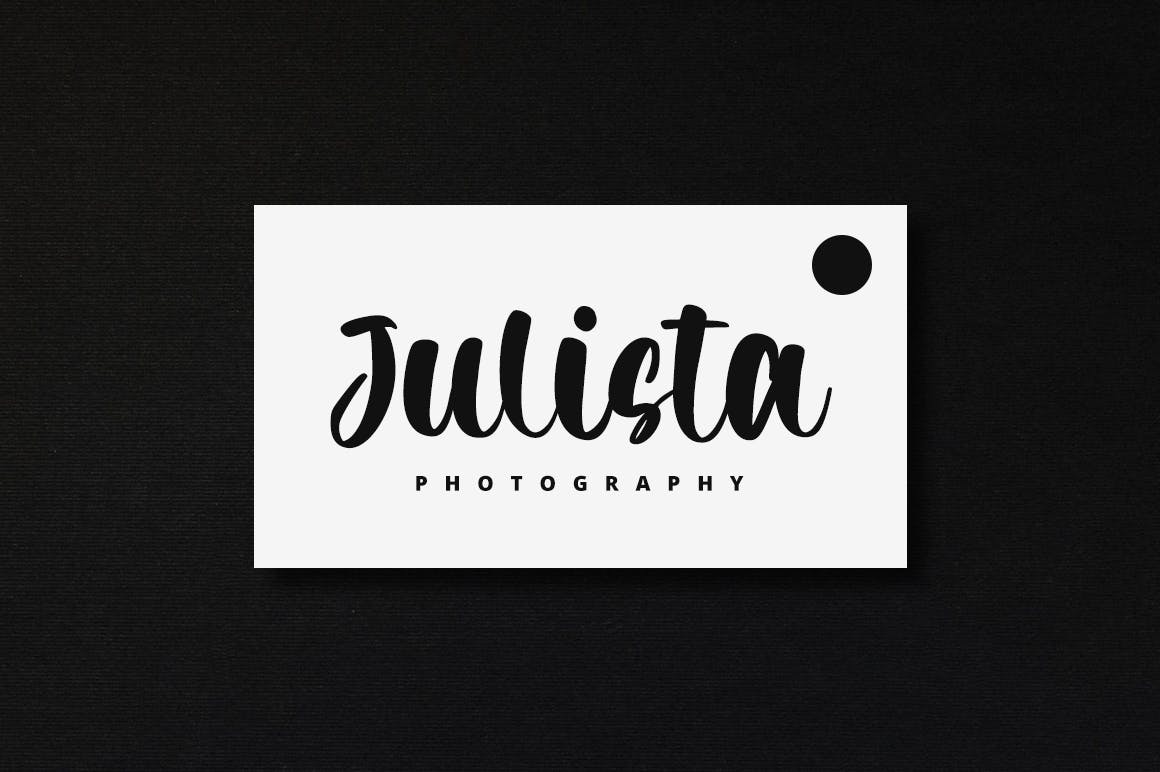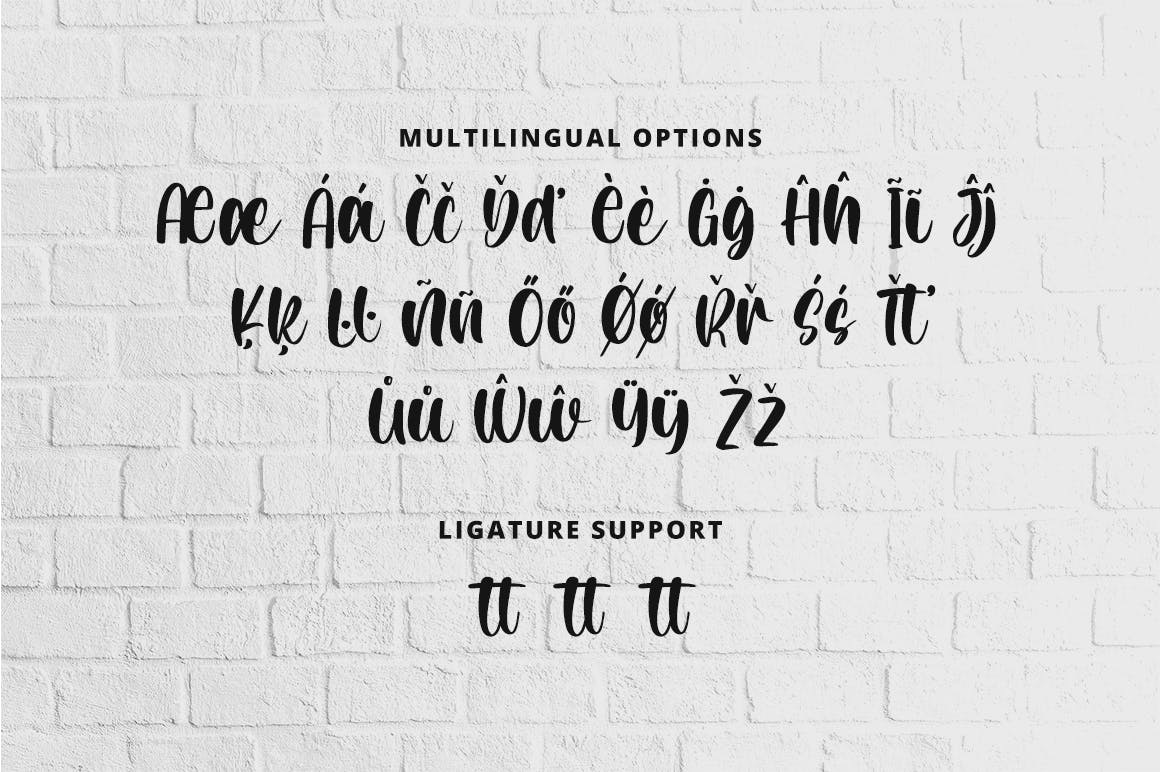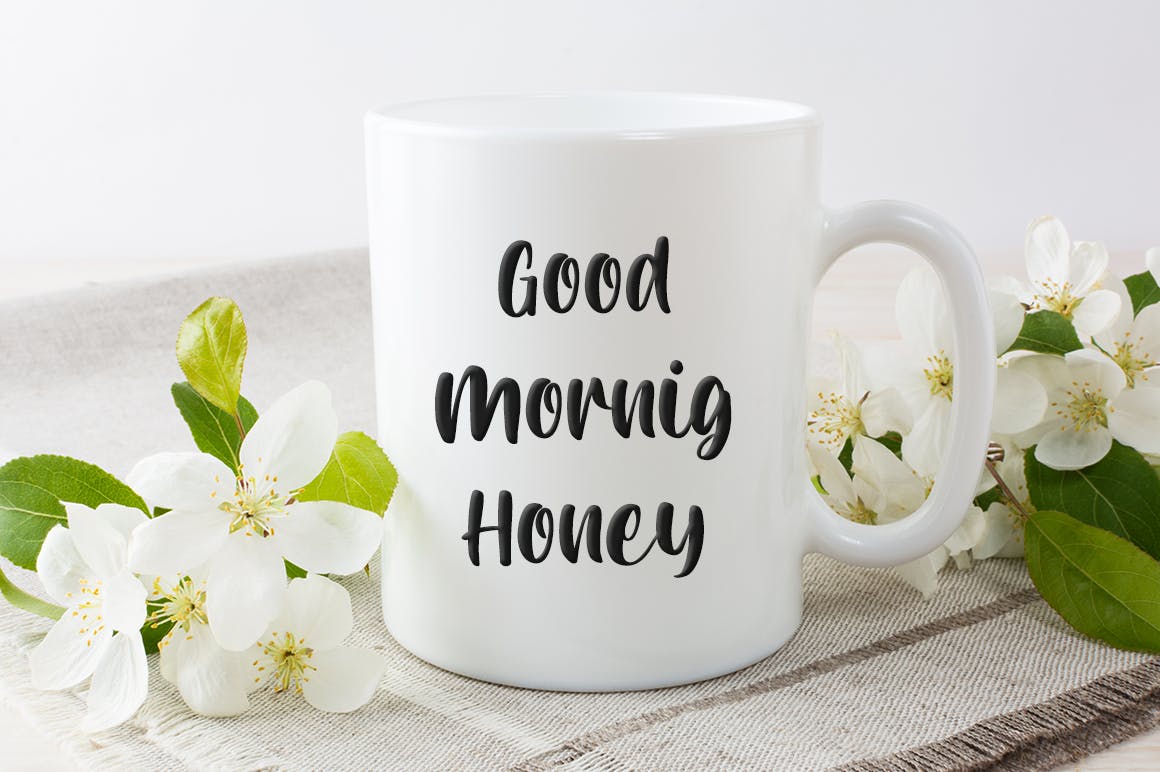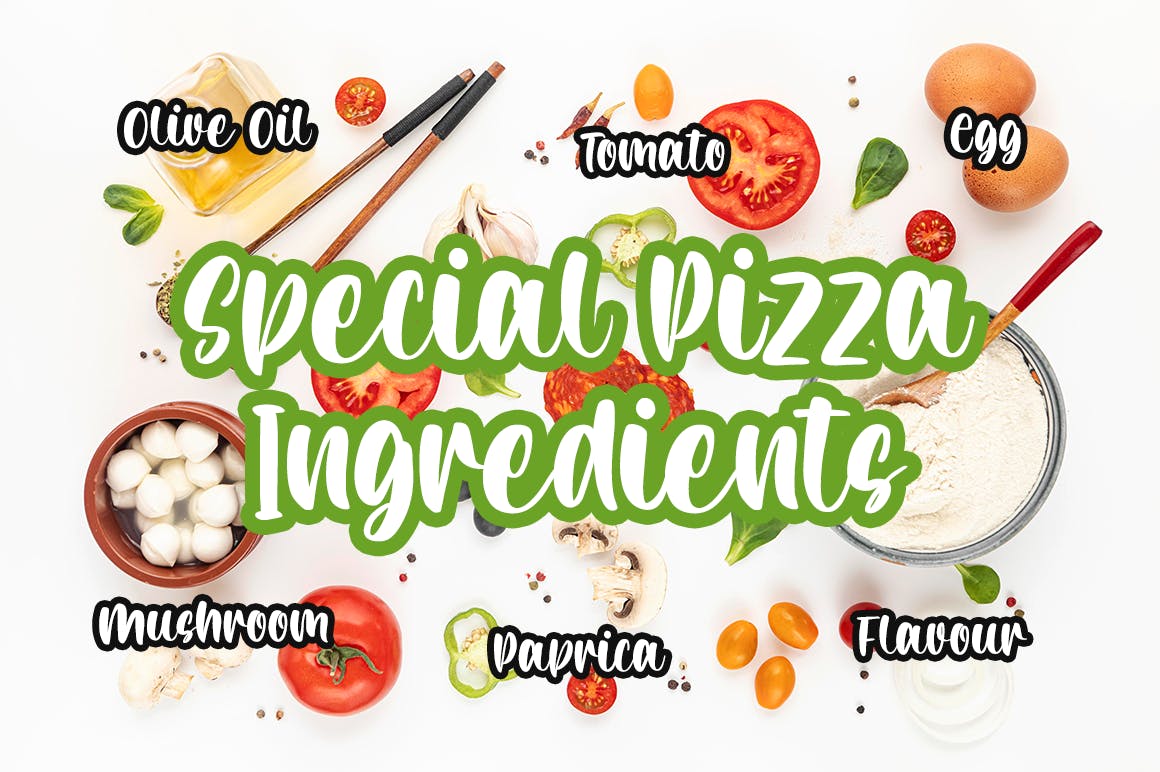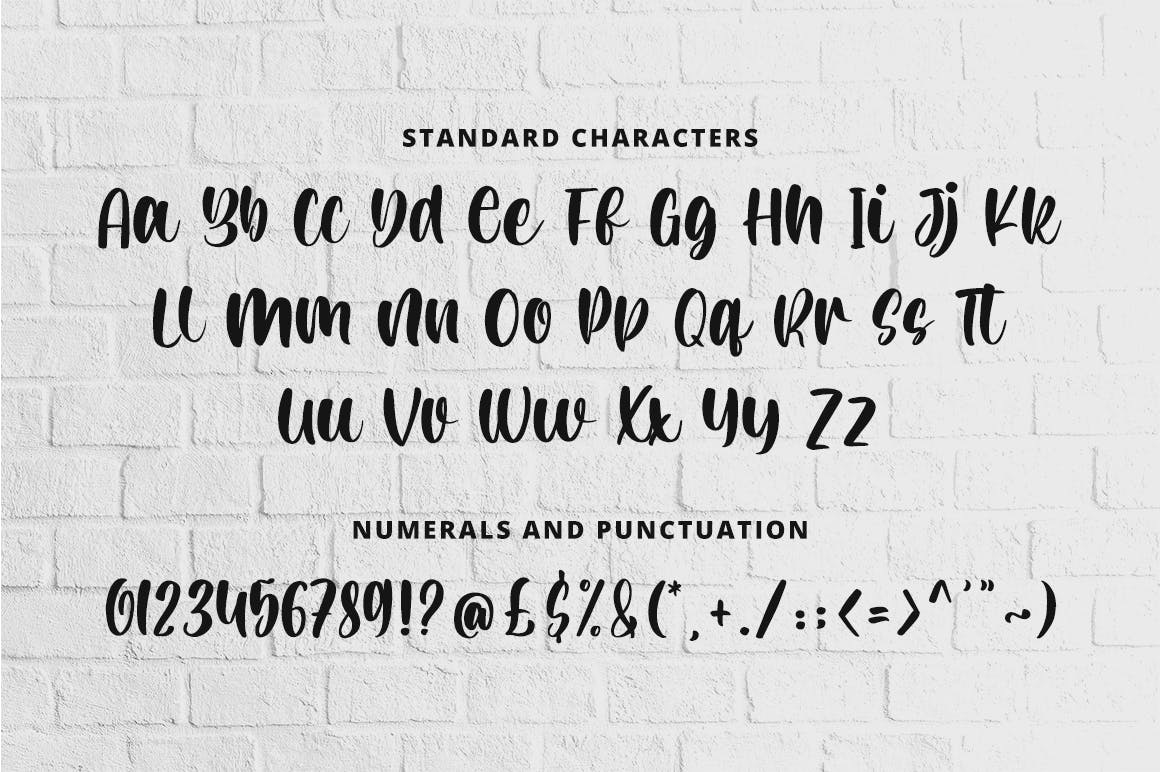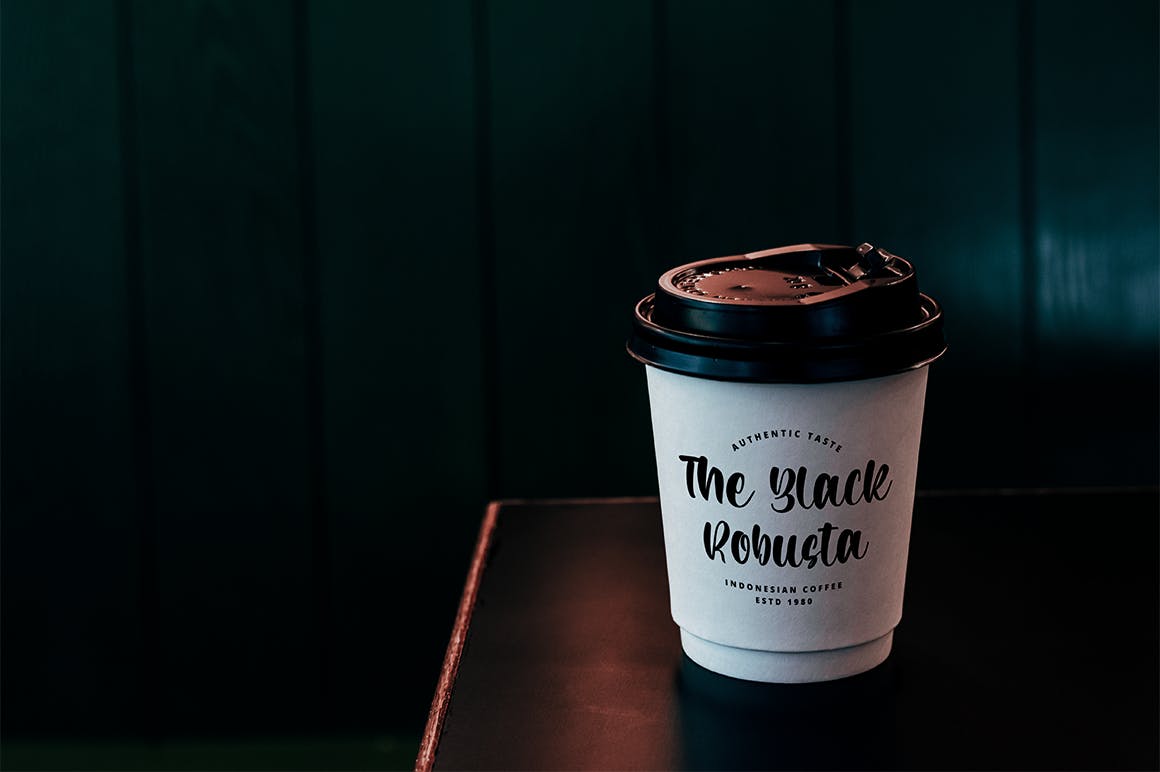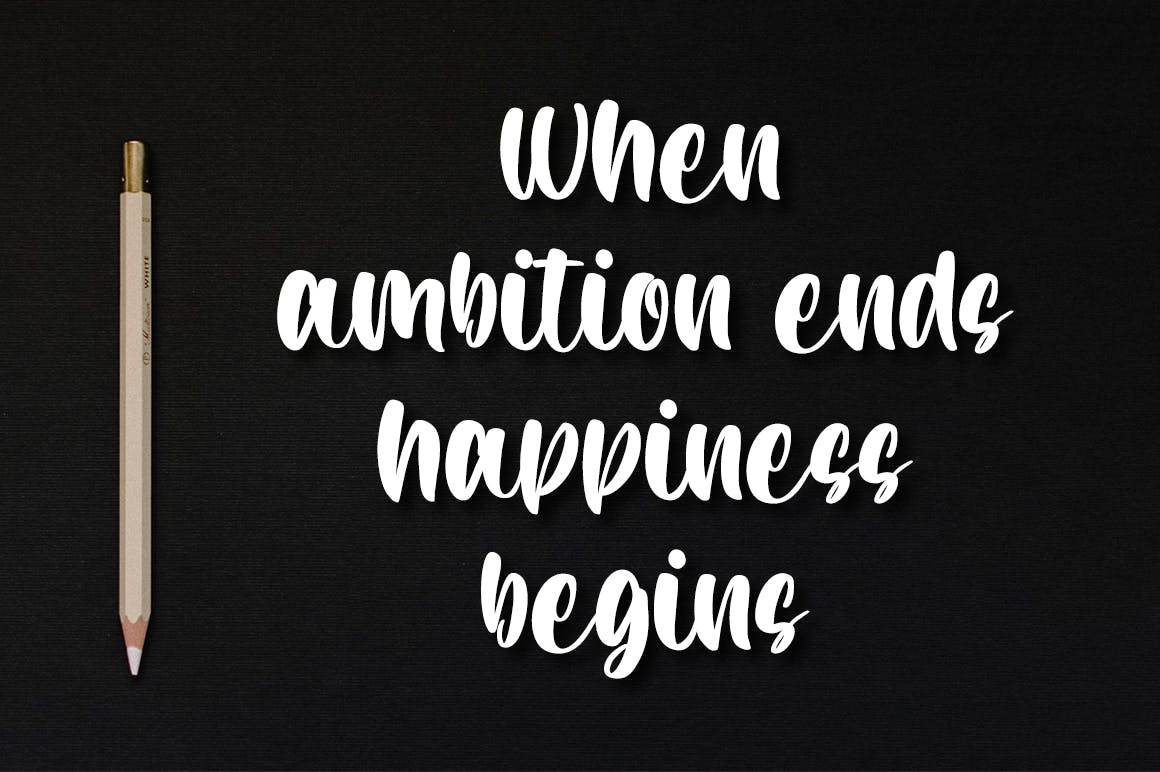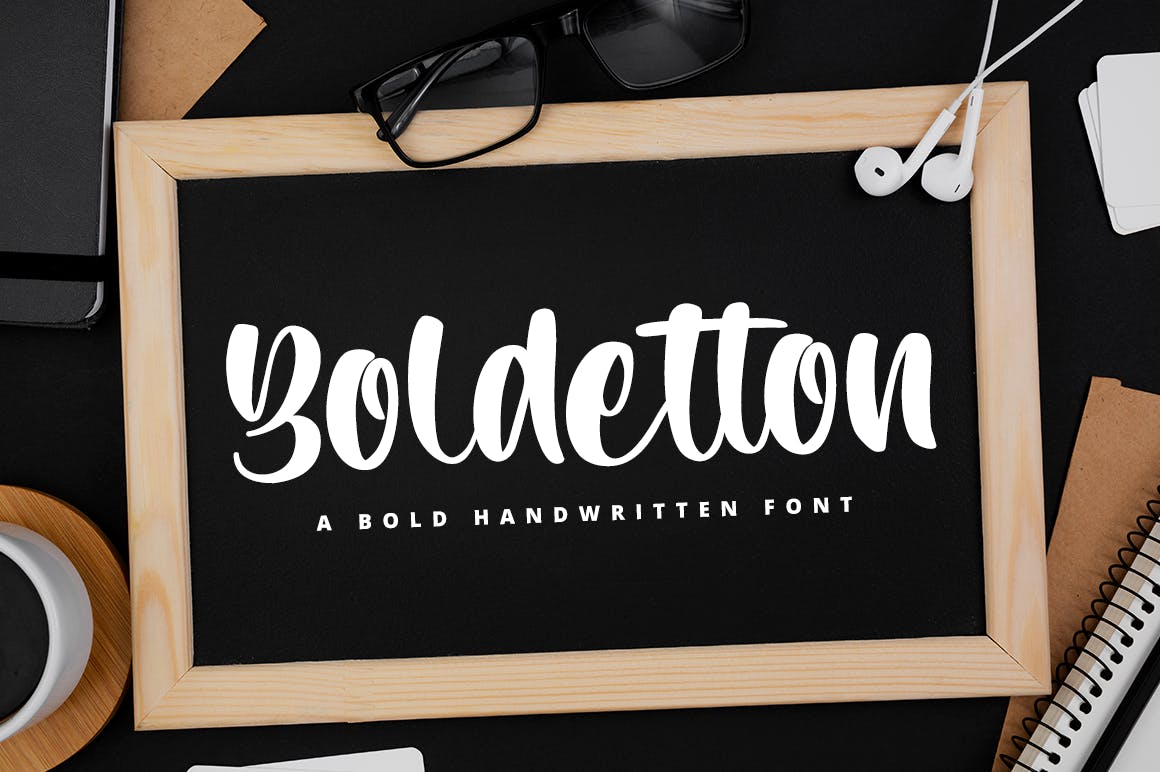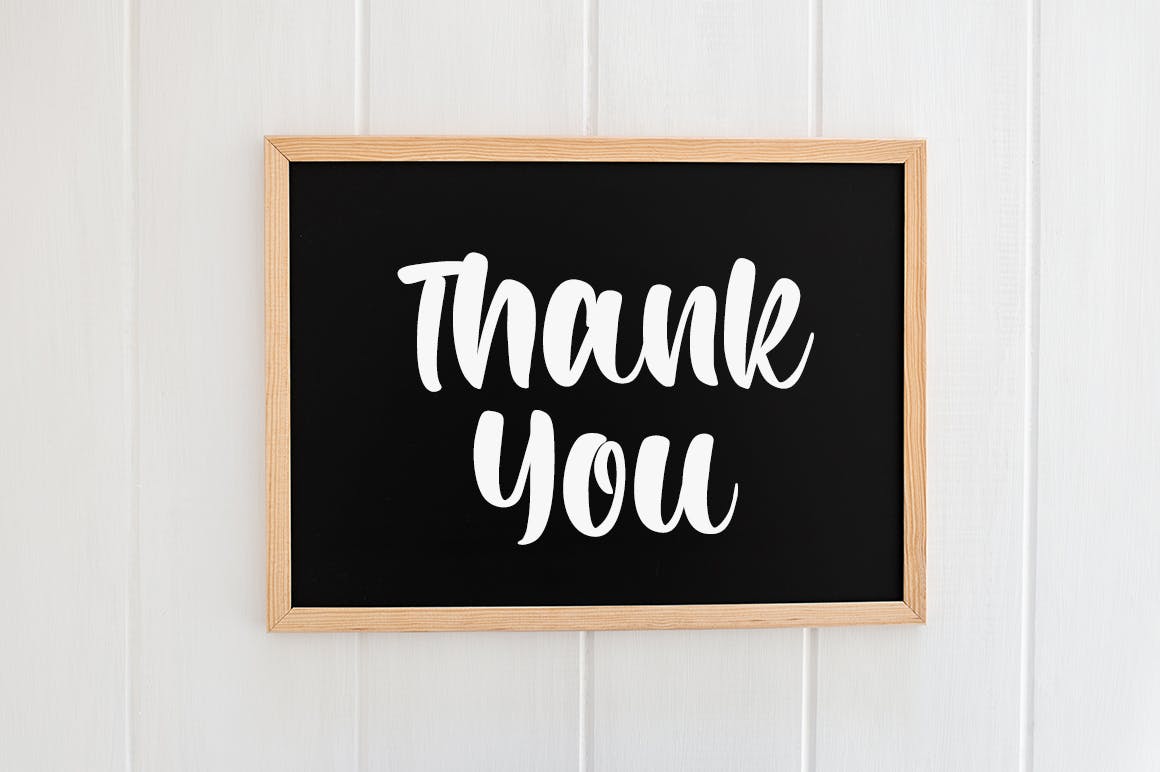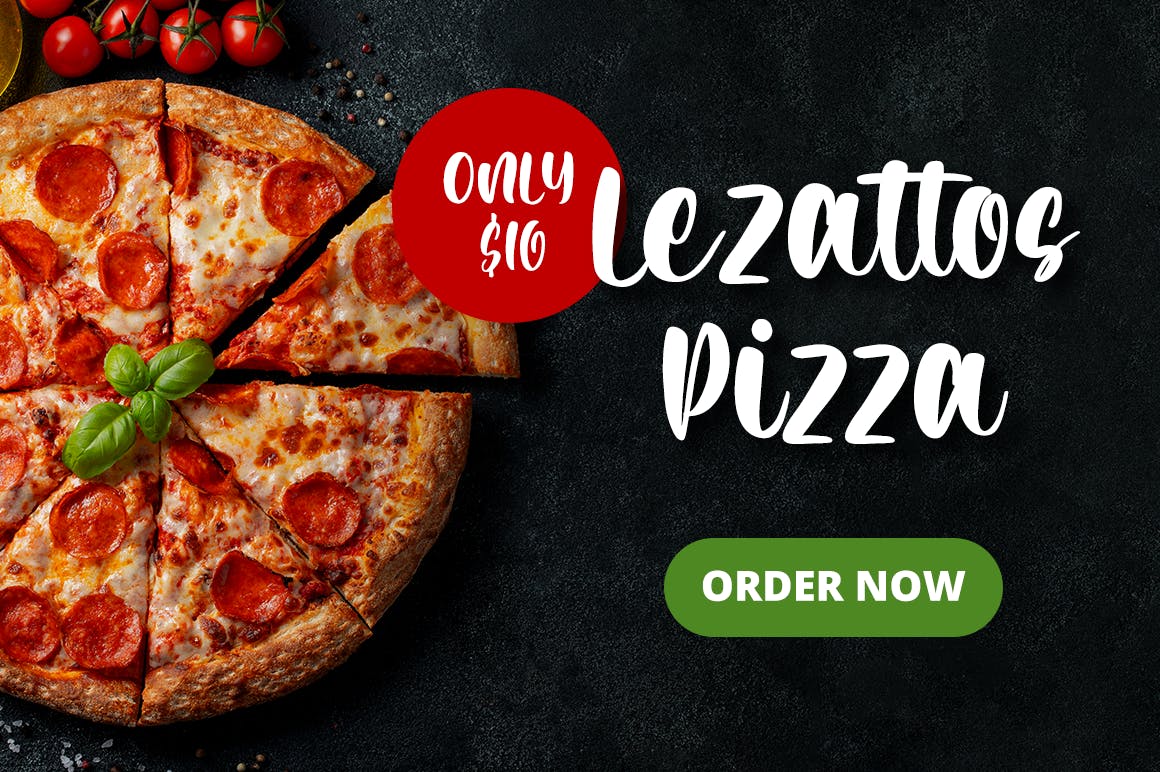
Boldetton یک فونت اسکریپت زیبا و برجسته است. با سبک فوقالعاده متنوع آن عاشق خواهید شد و میتوانید از آن برای ایجاد دعوتنامههای عروسی زیبا، هنرهای استیشنری جذاب، پستهای چشمنواز در شبکههای اجتماعی و موارد بسیار دیگر استفاده کنید!